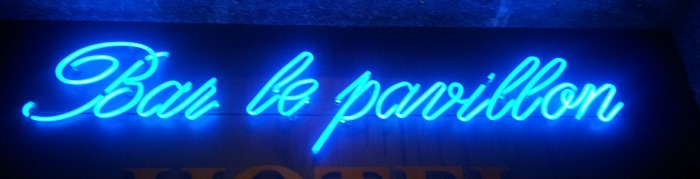
Schriftart von Leuchtreklame Bar
Ich suche die Schriftart oder ein möglichst ähnliches Pendant von einer Bar-Leuchtreklame. Habe es schon erfolglos mit diversen Schrifterkennungsdiensten wie whatthefont versucht.
Das ist ja keine Satzschrift, sondern so angelegt, dass man es in Röhren biegen kann.
Formelle Schreibschriften dieses Stils findest hier:
Wenn es eher um den Röhrenlook gehen soll: